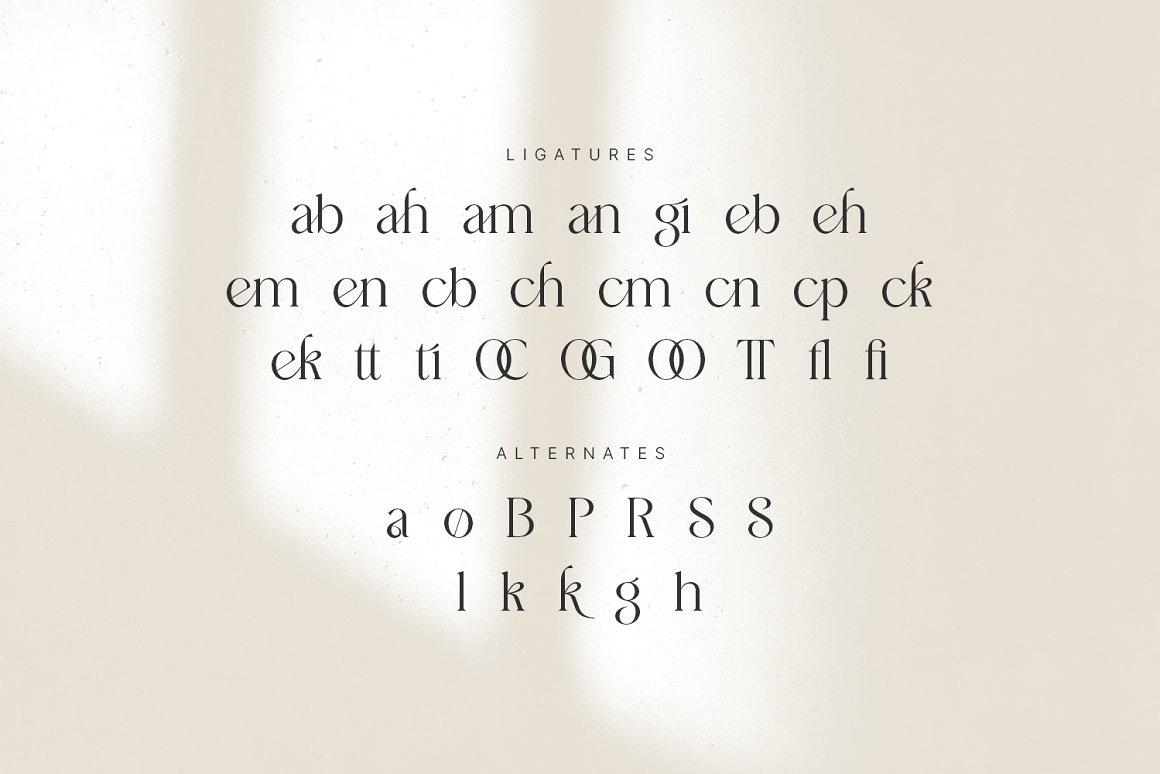
Westiga Font
Description de Westiga Font
Westiga est une police serif moderne et luxueuse conçue avec de magnifiques caractères conçus qui suivent la tendance. Il peut être utilisé pour ajouter une touche unique aux logos, aux en-têtes, aux activités de marque, aux magazines, aux emballages de produits, aux invitations, aux monogrammes, aux marchandises, au titre d’un livre d’affiches, au titre d’un film ou à des citations et bien plus encore.